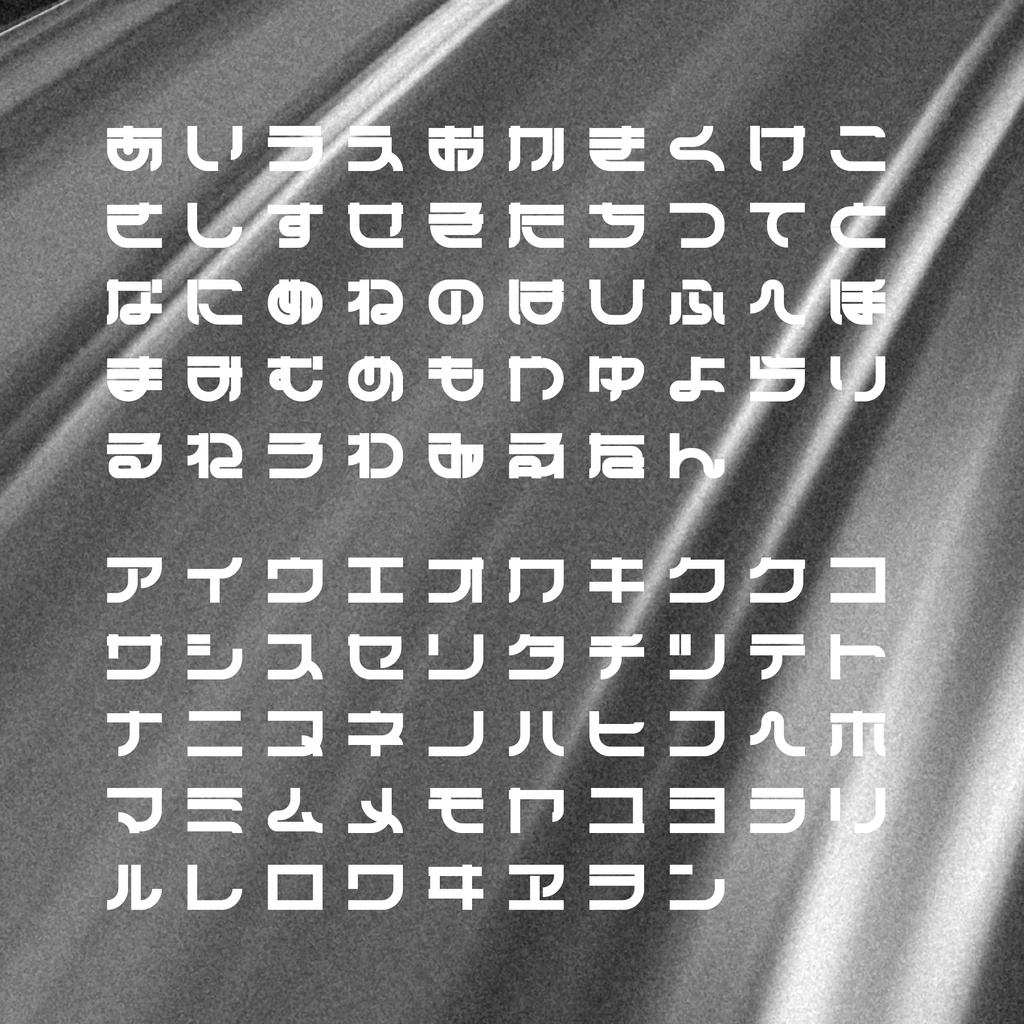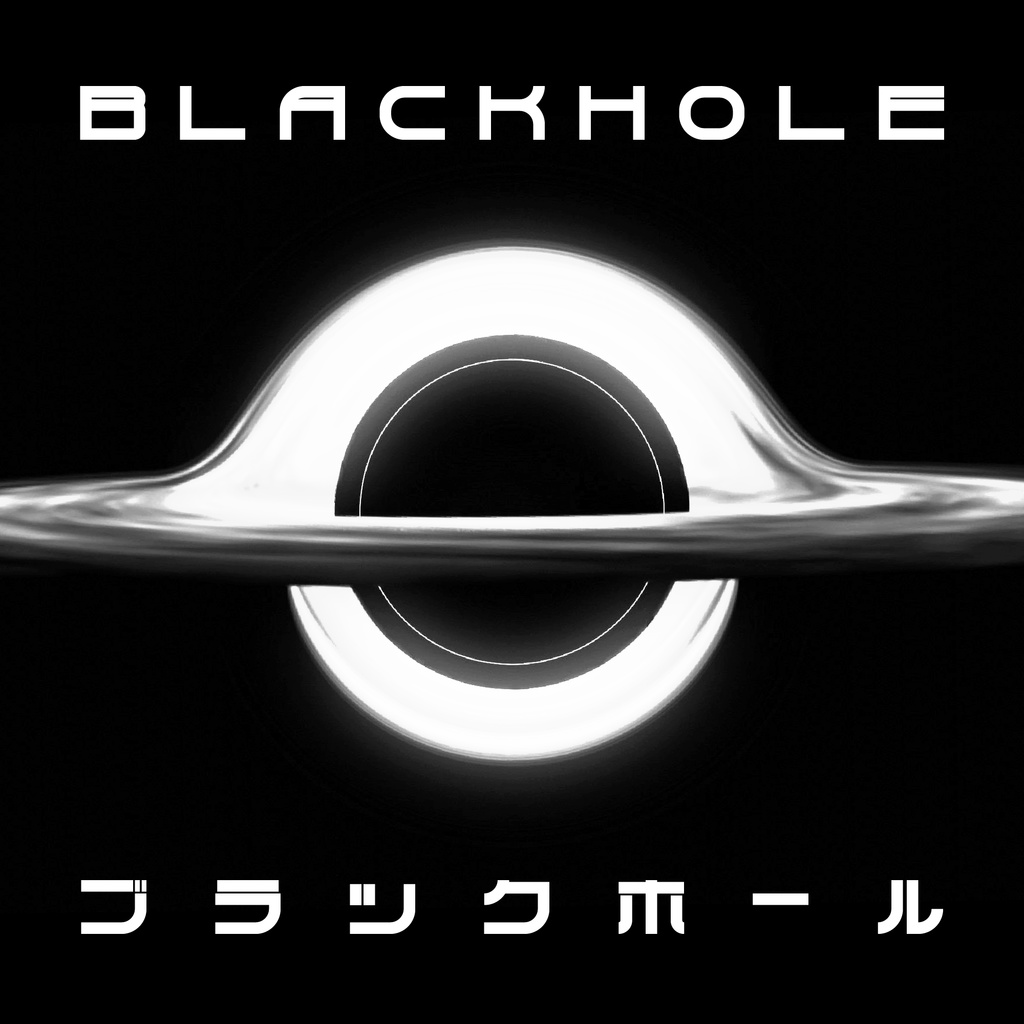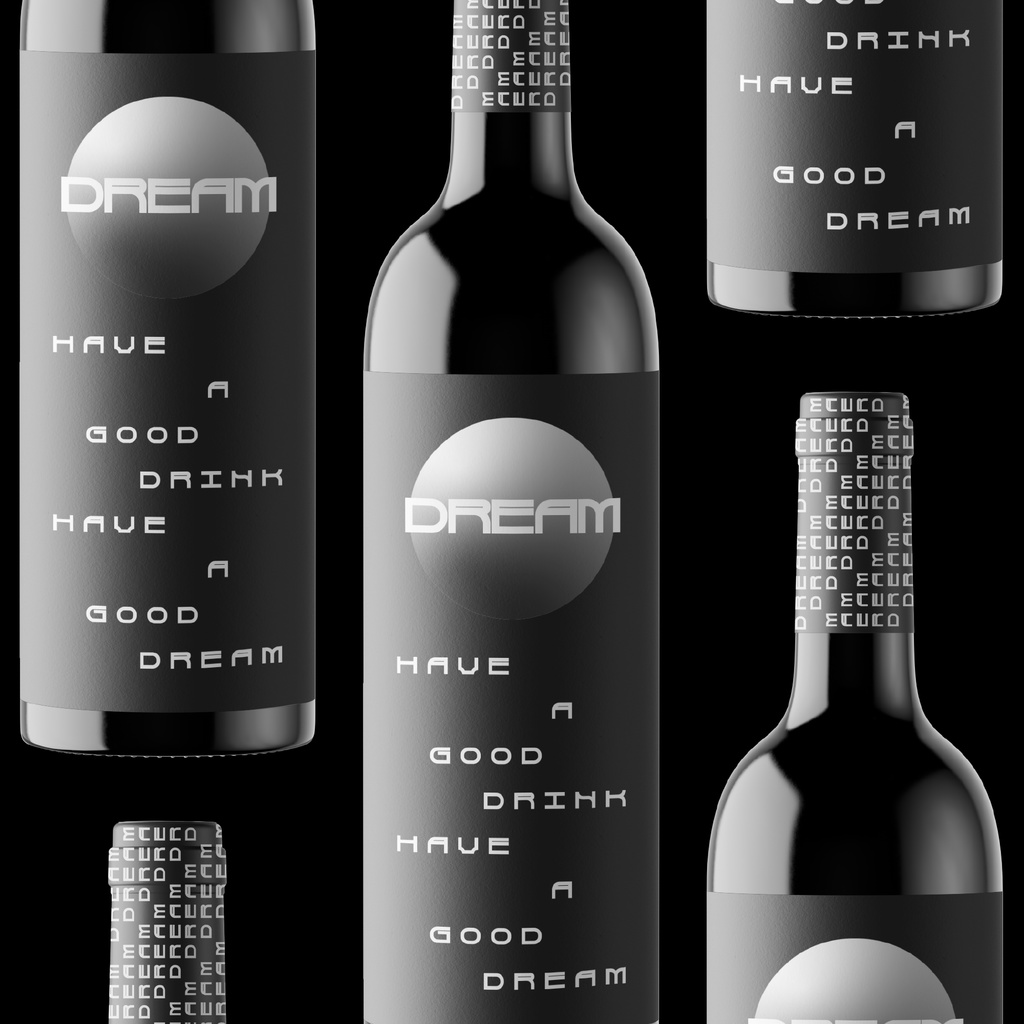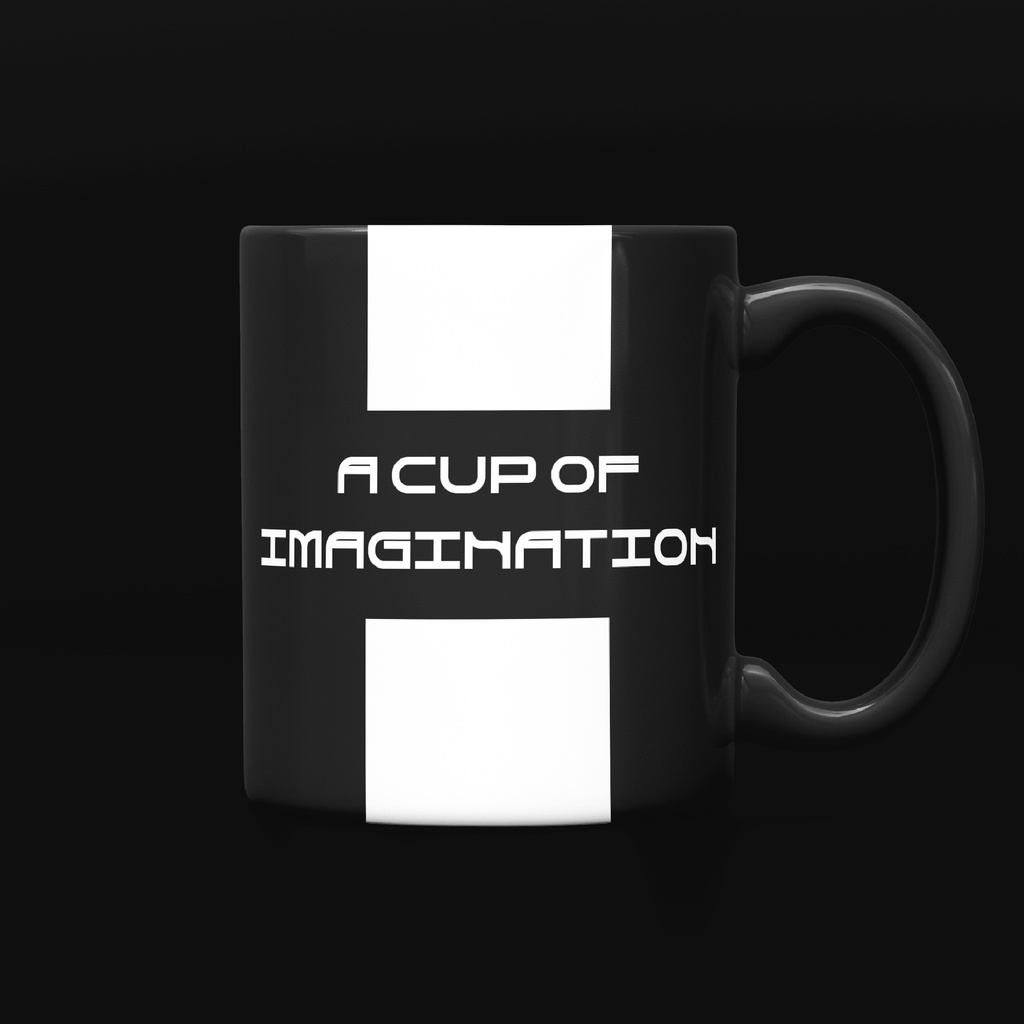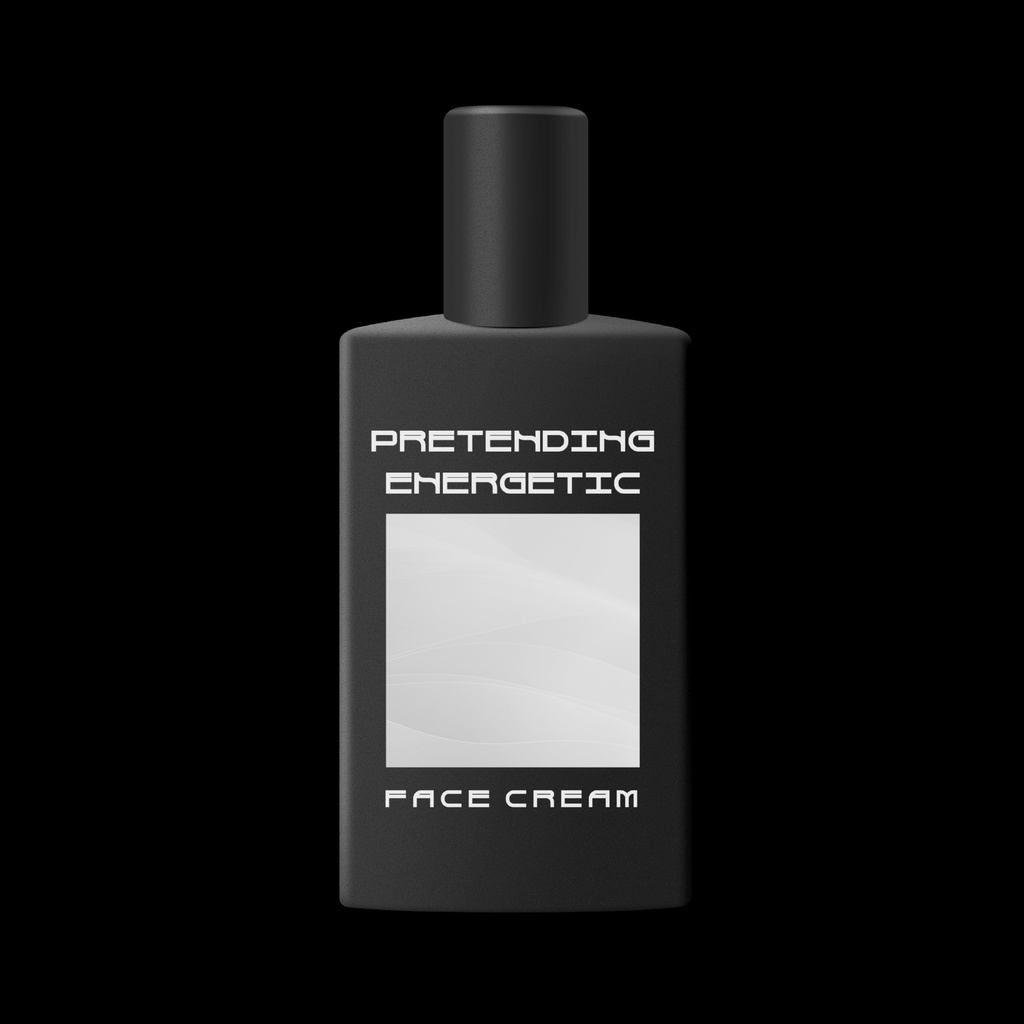
武力過剰 Force Overing「一時的に無料」 📢📢📢特記事項📢📢📢 このフォントは更新されない可能性があります。ご注意ください! 📢デザイン説明 武力過剰 Force Overingは今年の#1日1文字ひらがな作字の企画の拡張内容です。 このフォントは筆画を標準化することで各部分を統一し、ファンタジーとメカニックを同時に実現した近未来的な書体です。 12日間で制作されました。 📢利用規約 このフォントは無料でダウンロードできる。 個人、商用どちらでも利用可能です。 もしもこのフォントが使用されたら、https://twitter.com/amari_designに教えていただけるとうれしいです! 本素材を使用した作品については、リツイートなどの形で宣伝させていただく場合があります。 フォントのインストール等の技術的なサポートはいたしません。使用して発生したと思われる如何なる問題についても、作者は責任を負わないものとします。 著作権を放棄することはありません。 商標を登録したり、作者であると主張したり、データ自体を販売または再販したりすることは禁じられています。 このコンテンツの最終的な解釈権は作者に帰属します。 内容補充とバージョン更新は製作続けるです。使用する際は最新バージョンにご注意ください。 📢収録內容 武力過剰 Force Overingはラテン文字、仮名、数字だけてを含む287グリフが含まれています。 ーーーーーーーーーーーー Twitter:https://twitter.com/amari_design Behance:https://www.behance.net/9f45706b ーーーーーーーーーーーー